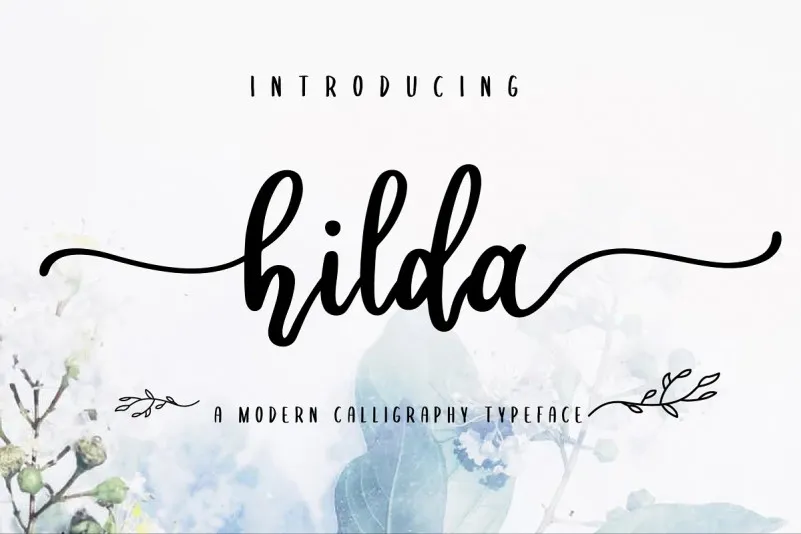
A Hilda Font é uma elegante linha de churrasco que traz alegria e sabor aos seus projetos artísticos modernos. Embora a descrição original sugira um estilo mais delicado, essa fonte inova na categoria de scripts, oferecendo uma aparência suave e versátil, ideal para quem busca adicionar um toque pessoal e sofisticado em suas criações digitais. Seja você criando gráficos de arte digital, editando textos ou desenvolvendo logos, a Hilda Font é perfeita para aqueles que buscam uma fonte elegante e moderna sem perder o charme do texto artesanal. Suave mas forte, essa font se destacará em qualquer projeto visual que você apresentar.